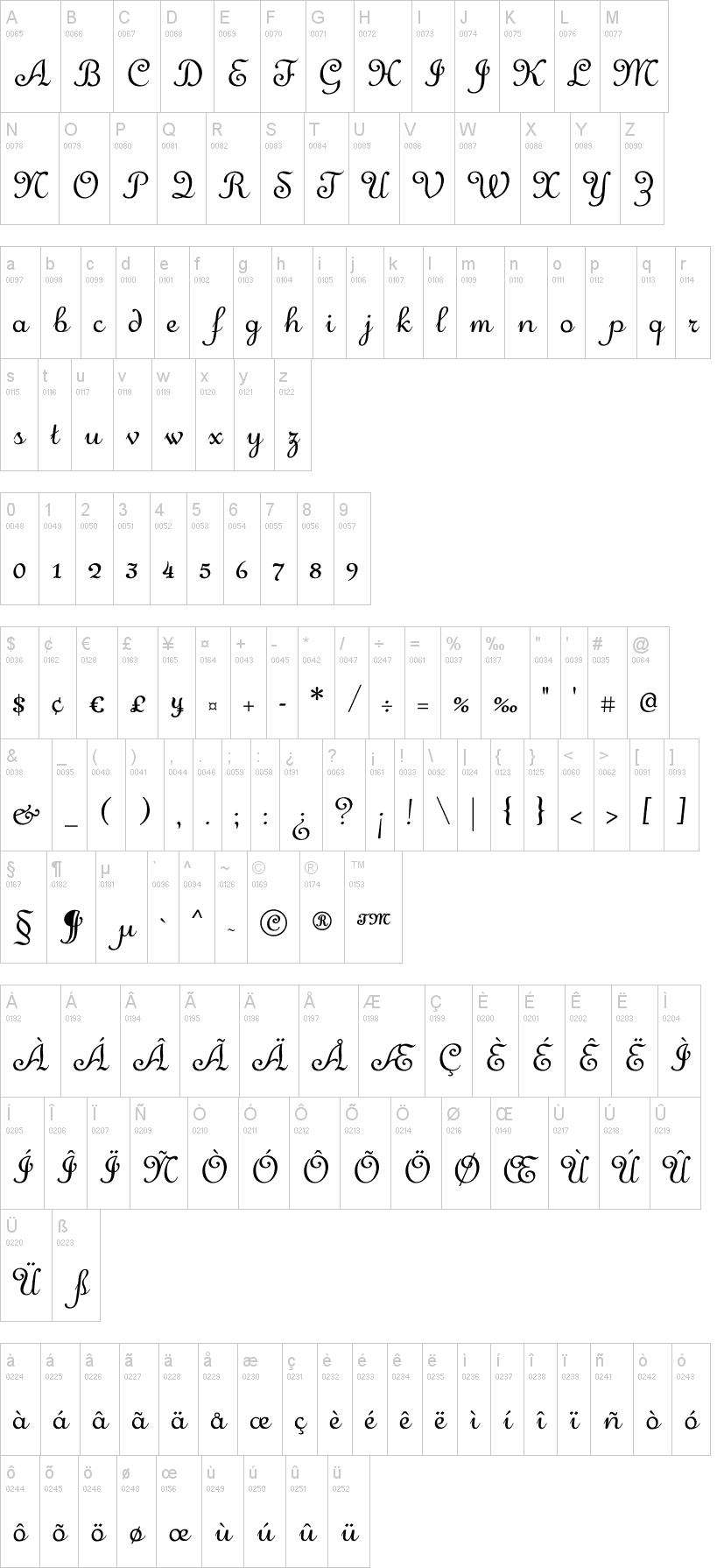
Merveille字体是一种古典字体,由著名的设计师Nicolas Cochin于1750年代创作。它具有古典的华丽外观,是一种经典的古典字体,可以用于各种印刷和设计项目,如书籍、海报、标志和广告等。Merveille字体具有流畅的线条和优美的曲线,使它非常适合用于拼写单词和句子。它还具有许多细节,如精细的笔画、刻线和拉丁文字,使其显得格外优雅。Merveille字体的字体大小可以调节,使其适合各种不同的应用场景。内容介绍
Merveille是一款非常不错的手写艺术字体,具有很好的视觉感,适合于文化类的宣传设计、商业类品牌的广告和产品包装设计以及个性化文字排版等较多场景。